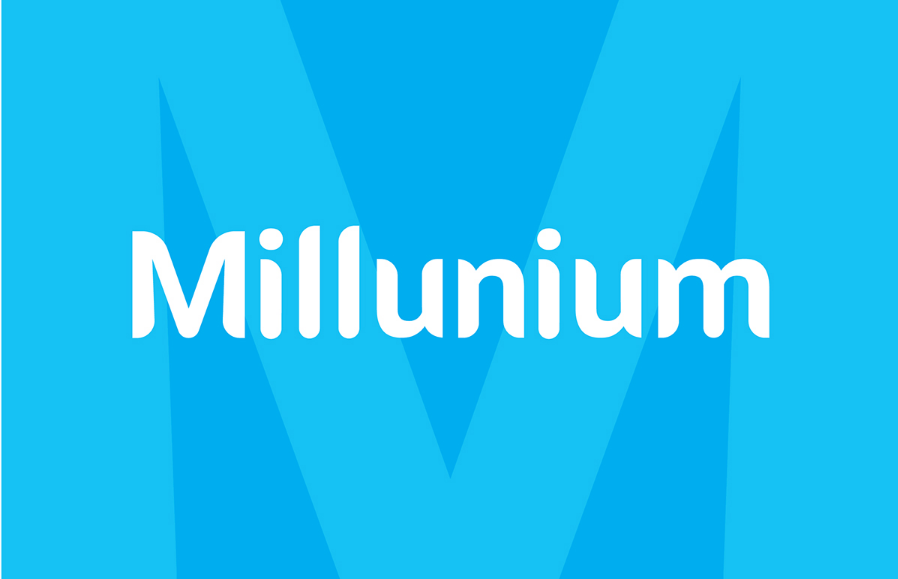
Millunium Typeface – Fonte Grátis
Millunium Typeface
Millunium é uma tipografia sans-serif contemporânea projetada para se alinhar com as tendências atuais do design. Perfeita para diversos tipos de projetos, desde logotipos até a tipografia principal e para aplicativos de materiais publicitários, essa fonte apresenta quatro pesos (leve, normal, bold e negro) e quatro itálicos. Com sua refinada qualidade de produção, Millunium se destaca como uma opção ideal para designers. Suas linhas modernas e elegantes atraem olhares, tornando-a perfeitamente adequada para aplicativos em materiais publicitários, desde cartazes até roupas. Seu design único permite que seja usada em uma ampla gama de projetos gráficos sem perder seu brilho e simplicidade moderna. Millunium é um recurso valioso para designers digitais e imprensa. É perfeita para criar identidades visuais sofisticadas, desde logotipos a revistas de moda, além de aplicações em materiais publicitários como cartazes e adesivos. Ela também se destaca nas mídias sociais e em designs digitais, mantendo sua simplicidade e modernidade enquanto complementam os recursos gráficos de projetos digitais. Millunium é uma ótima escolha para qualquer designer que busca um design moderno e forte, com a facilidade de uso que só Hamilton pode oferecer.